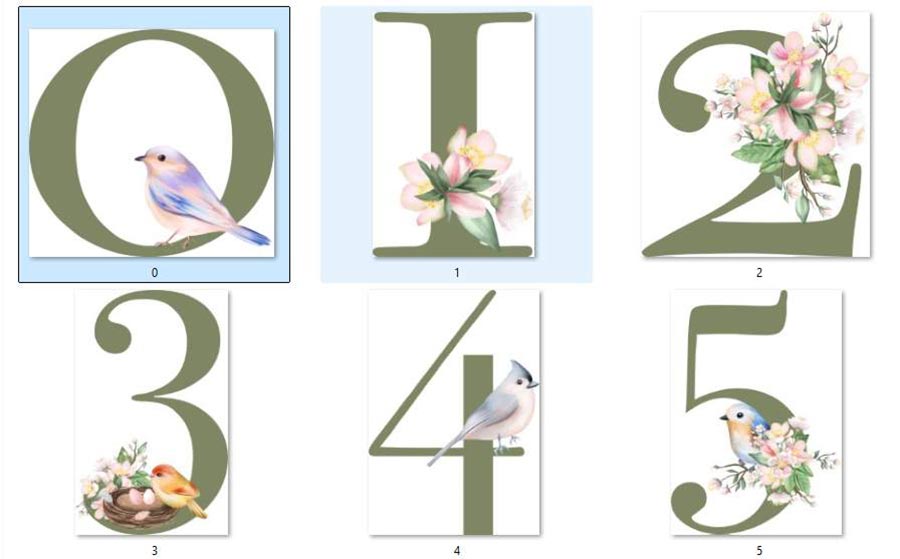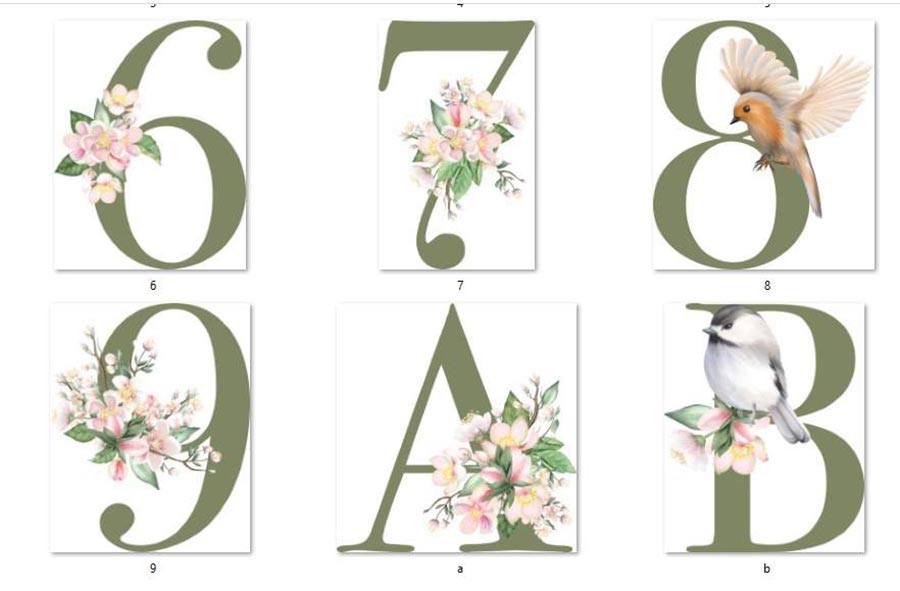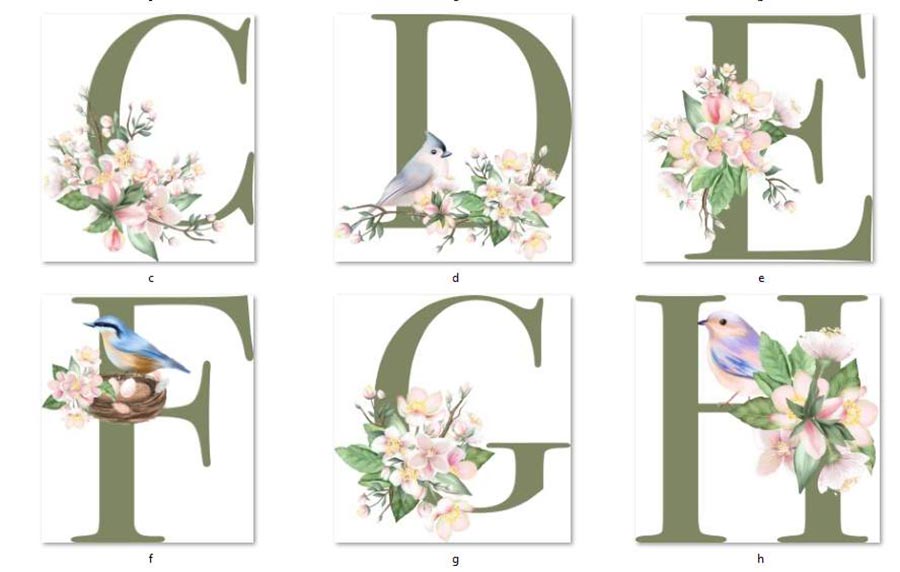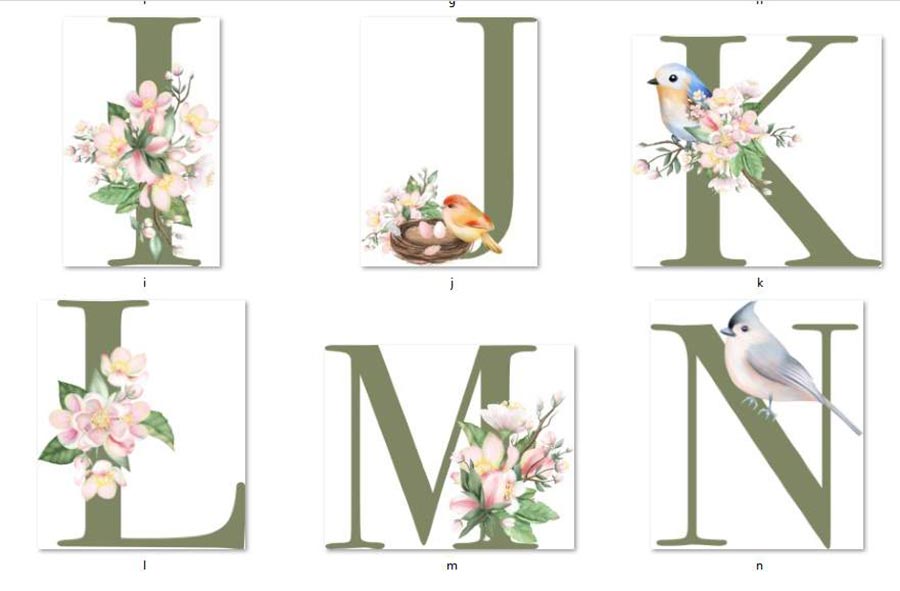
Chia Sẻ Bộ Font Chữ Mùa Xuân Tuyệt Đẹp Miễn Phí
Bộ Font Chữ Mùa Xuân Tuyệt Đẹp là lựa chọn hoàn hảo để thổi hồn cho các thiết kế của bạn, sẽ mang đến cảm giác tràn đầy sức sống và sự tươi mới nhất.Sadesign hi vọng với phong cách mềm mại, bay bổng, bộ font này sẽ làm nổi bật mọi dự án sáng tạo của bạn. Khám phá bộ font chữ mùa xuân tuyệt đẹp tại sadesign.vn để làm mới thiết kế của bạn. Hoàn toàn miễn phí, dễ dàng tải về và sử dụng ngay hôm nay.
1. Ý nghĩa của font chữ mùa xuân trong thiết kế
Font chữ mùa xuân không chỉ đơn thuần là kiểu chữ mà còn truyền tải cảm xúc và thông điệp. Những đường nét mềm mại, phóng khoáng thể hiện tinh thần lạc quan, sự tươi trẻ và tràn đầy sức sống.
• Mang lại sức sống mới: Các kiểu chữ được thiết kế để khơi gợi cảm giác tươi mới, phù hợp với không khí mùa xuân.
• Tăng tính thẩm mỹ: Font chữ mùa xuân thường sử dụng các đường cong tinh tế, tạo sự hài hòa trong thiết kế.
• Phù hợp với nhiều chủ đề: Từ thiệp mời, banner quảng cáo, đến các bài đăng mạng xã hội, font chữ mùa xuân đều giúp tạo điểm nhấn thu hút.
2. Đặc điểm nổi bật của bộ font mùa xuân tại Sadesign.vn
SaDesign.vn đã tuyển chọn kỹ lưỡng để mang đến bộ font mùa xuân đáp ứng mọi nhu cầu sáng tạo:
• Đa dạng phong cách: Bộ font bao gồm các kiểu chữ tay mềm mại, chữ viết hoa cách điệu, và cả những thiết kế hiện đại, cá tính.
• Hỗ trợ sáng tạo: Phù hợp để tạo các sản phẩm như thiệp chúc mừng, bìa sách, và banner quảng cáo.
4. Ứng dụng của bộ font chữ mùa xuân trong thiết kế
Bộ font mùa xuân mang lại nhiều lợi ích trong việc làm mới các dự án thiết kế:
Thiết kế thiệp chúc mừng
Các đường nét uyển chuyển, màu sắc sinh động từ font chữ mùa xuân giúp tạo nên những tấm thiệp đầy cảm xúc, phù hợp cho dịp Tết hoặc các sự kiện đầu năm.
Banner quảng cáo và poster
Với phong cách độc đáo, font mùa xuân giúp truyền tải thông điệp nhanh chóng và thu hút sự chú ý của khách hàng.
Nội dung mạng xã hội
Hình ảnh được thiết kế với font chữ mùa xuân tạo sự khác biệt, giúp tăng tương tác trên các nền tảng như Facebook, Instagram, hoặc TikTok.
Bao bì sản phẩm
Đối với các thương hiệu kinh doanh sản phẩm mùa xuân như bánh kẹo, hoa, hoặc đồ trang trí, bộ font này mang lại hiệu quả quảng bá cao.